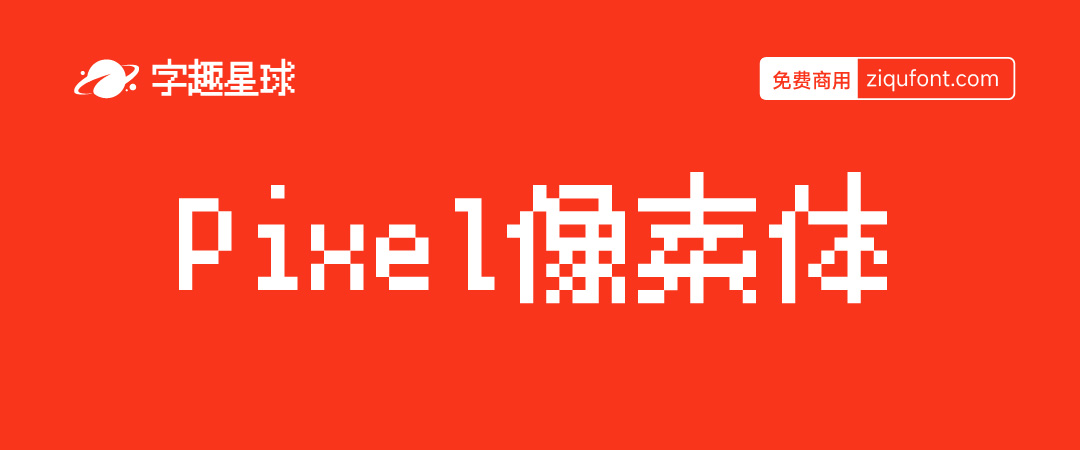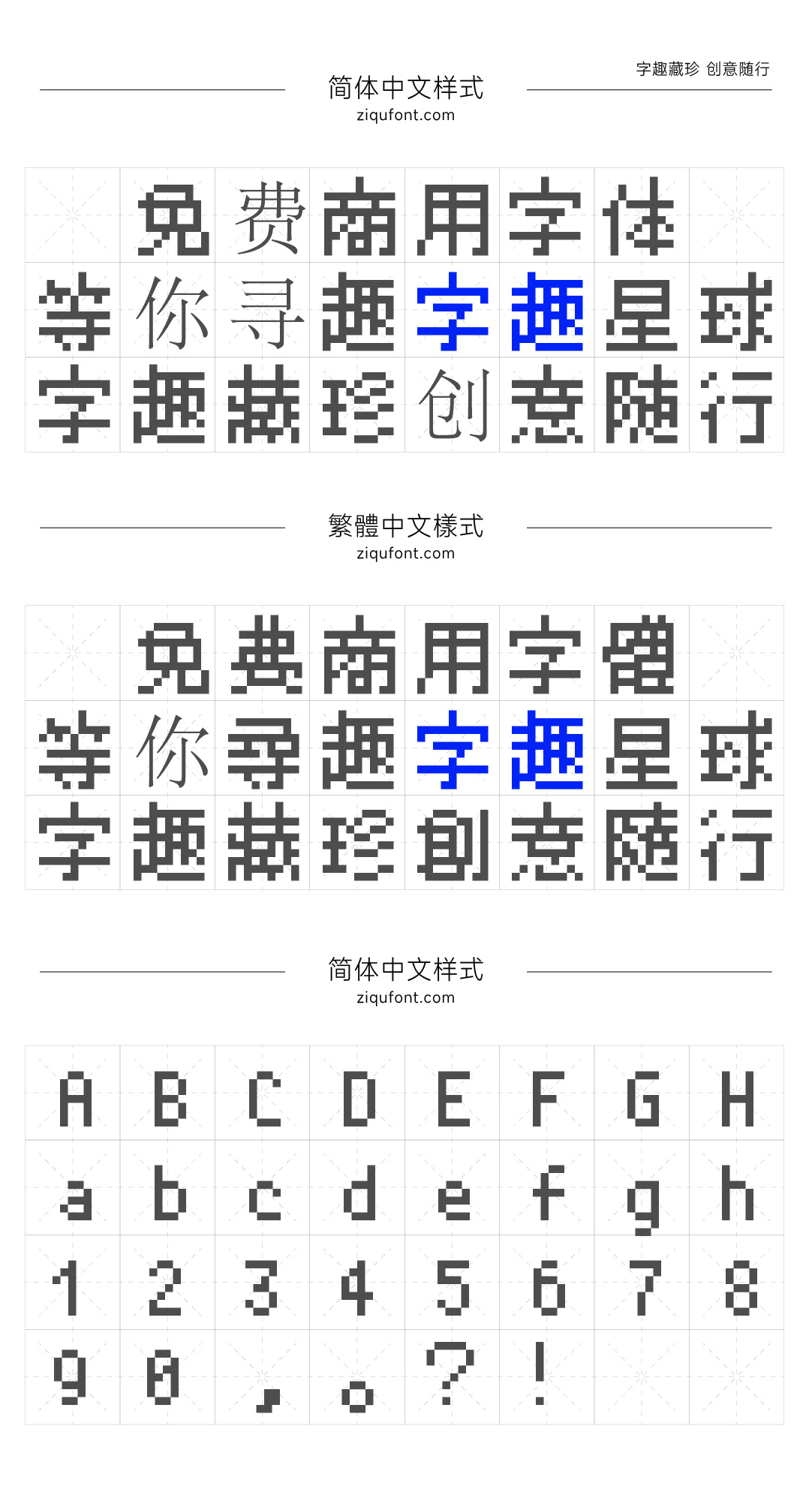
PixelMplus-像8bit游戏机的日本点阵像素字体
字体介绍
PixelMplus(ピクセル・エムプラス)是一款TrueType轮廓字体,让人感觉像是8bit风格的点阵像素字体。但只有轮廓,没有嵌入位图,包括粗体。收录了JIS第1、第2水准的所有字符,还收录了ISO-8859-1(Latin-1)的字符,除此之外还追加了一些其他符号。它实际是一个TrueType等宽字体,也可以在文本编辑器中使用。有PixelMplus12和PixelMplus10两种字体,区别在于原始位图字体是12像素还是10像素,两者的大小相同。